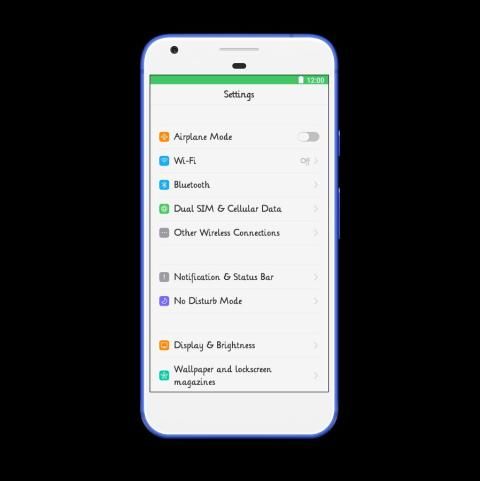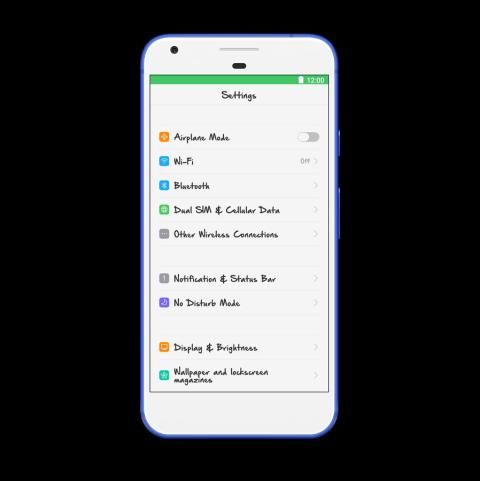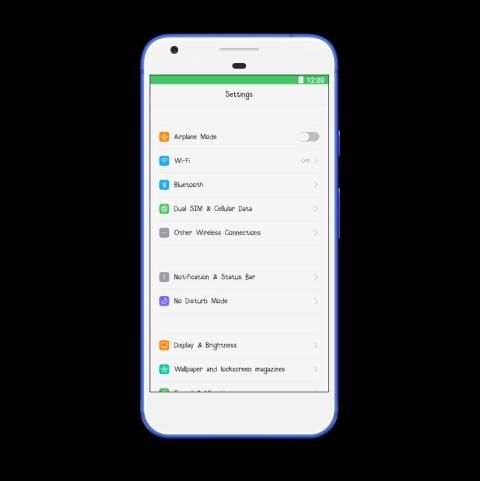
Ini adalah paket fantastis font tulisan tangan untuk ponsel OPPO Anda. Nikmati tampilan baru dan merasa dengan berbagai font tulisan tangan dalam paket.